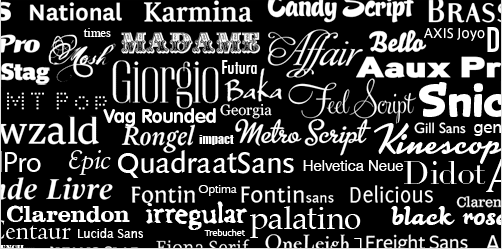
Каким должен быть шрифт для сайта?
Всем привет! Правильный выбор шрифта — это важный момент для дизайнеров и веб-мастеров. Сегодня дизайнеры могут выбрать любой понравившийся шрифт из огромного списка. Но есть проблема, которая заключается в выборе нужного шрифта. Для того, чтобы найти подходящий шрифт, уходит масса времени, а еще и новые шрифты появляются каждый день.
Пользователям, которые давно в интернете (дизайнеры, владельцы сайтов и блогов со стажем) уже знают как правильно подобрать нужный шрифт , так как у них есть определенный опыт. А что делать новичкам? Какой шрифт выбрать для своей странички? Как использовать нестандартные шрифты, чтобы было красиво? Об этом я хочу рассказать в этом посте.
Как будет читаться информация на странице и захочет ли пользователь ее читать, зависит от правильно выбранного шрифта. От слишком мелкого шрифта посетителям вашего ресурса придется напрягать глаза и сидеть впритык к монитору, от более крупного шрифта рассредотачивается внимание и придется постоянно искать текст.
Текст на странице не должен быть слишком большим, с длинными предложениями и без абзацев. Обязательно надо разбивать весь текст на несколько абзацев и пунктов, так как весь текст сливается и, если вы отвлечетесь от чтения, потом будет сложно найти на чем вы остановились.
Как выбрать шрифт?
Многие шрифты уже по умолчанию установлены на наших компьютерах и ноутбуках. Это такие шрифты, как: Arial, Georgia, Comic Sans MS, Times New Roman, Verdana, Tahoma и другие. Но если вы будете устанавливать нестандартный шрифт на сайт, следует помнить, что у посетителей вашего сайта может не оказаться такого шрифта, и страница будет отображаться не так, как вы задумали.
Важно учитывать такие детали шрифта: вес, засечки, кернинг (интервал между буквами), высоту выступов и линии выравнивания. Дизайнер должен обдуманно выбирать шрифт для сайта и знать, какой именно тип шрифта применить под разрабатываемый сайт.
В случае, если вам нужно что-то нестандартное, типо заголовка, красивой надписи или кнопок, лучше сделать это изображением, в формате gif или jpg. Таким образом, например, можно сделать красивое название сайта рядом с логотипом, и такой текст у всех пользователей будет смотреться одинаково.
Если вы хотите, чтобы посетителям вашего сайта или блога было комфортно находится на страничке и люди читали ваш текст, нужно подобрать легко читаемый шрифт . Но тут не стоит перебарщивать, на сайте должно быть максимум 3-4 разный вида шрифтов.
Размер шрифта
Предпочтения у каждого человека свои. Самая используемая гарнитура шрифта это 10-12 , если шрифт мельче, то это, как я писала выше, не очень уважительно к посетителям, которые должны напрягать глаза при чтении, но и больший шрифт не подойдет, так как страница будет выглядеть как транспарант.
Мелкий шрифт чаще всего используется для примечаний или надписей под изображениями. Гарнитура таких надписей примерно от 8 до 10 . Заголовки и подзаголовки следует писать крупным размером шрифта, а так же не забывать выделять ключевые слова жирным текстом , подчеркиванием или наклоном.
Последние два варианта использовать не рекомендуется, так как пользователям сложно будет читать информацию. Подчеркиванием или наклоном можно выделить слово, предложение или заголовок, но никак весь текст. Еще подчеркиванием выделяю ссылки, например «Как вести свой блог«, чтобы посетители видели что это ссылка.
Цвет шрифта
Как правильно выбрать цвет шрифта? Классический вариант это черный шрифт на белом фоне . Можно использовать темно-серый (синий) вместо черного, так как черный иногда выглядит очень резко. Особенно если яркость монитора большая. Но это сугубо мое мнение.
Не следует делать яркие, кричащие цвета, а-ля синий фон и красный текст.
Цвета должны быть нейтральными, приятными для чтения, что бы глаза посетителей не уставали.
Выделить другим цветом можно, опять же, заголовок или ссылку.
Сглаживание шрифта
В таких браузерах как InternetExplorer и Safari уже включено сглаживание шрифтов по умолчанию, это касается и маленьких и больших шрифтов. В остальных браузерах Opera, Mozilla, сглаживание начинается с 17-18 px., а мелкий текст остается без сглаживания.
В идеале должно выглядеть вот так:
Шрифты используемые в веб-дизайне
Arial. Компактный шрифт, имеет преимущество благодаря высоте букв.
Tahoma. Подходит больше для технической тематики, имеет средне-широкие буквы.
Verdana. Хороший вариант использования шрифта для сайта. Будет хорошо и удобно читаться, благодаря ширине букв и между буквенном расстоянии.
Trebuchet MS. Не совсем подходит для чтения, даже при 12 px. приходится напрягать глаза.
Times New Roman. Шрифт имеет хорошую читаемость, используется во всех редакторах. Но при 12 px выглядит мелко.
В заключение, лучшие шрифты HTML для веб-сайтов
Веб-шрифты HTML позволяют веб-сайтам выглядеть одинаково на разных устройствах. Однако вы можете найти веб-шрифт, представляющий ваш веб-сайт. Это создаст формальный, профессиональный, современный или все, что вы хотите.